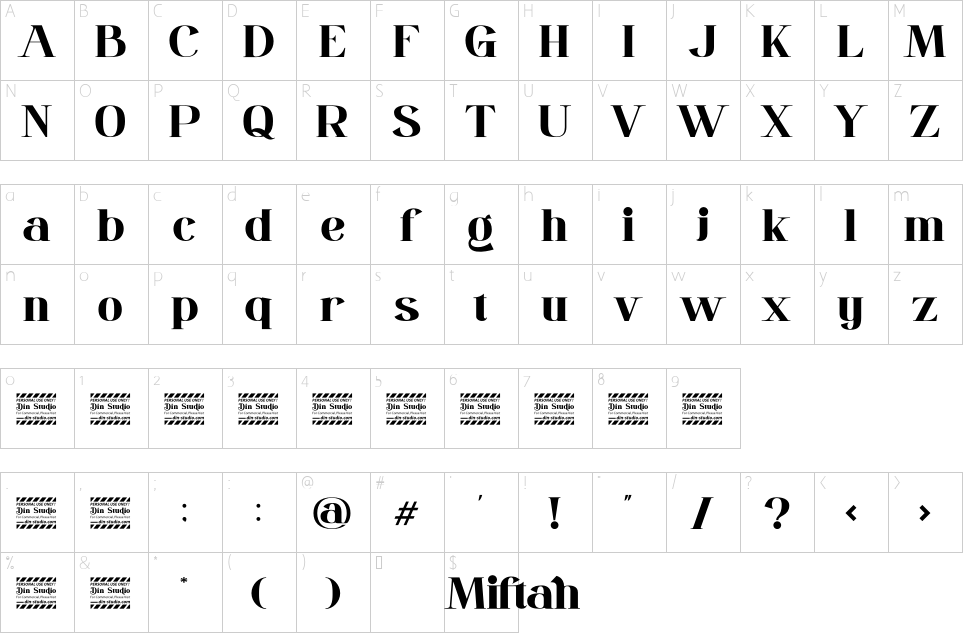
Descobrir uma nova fonte pode ser como uma aventura no mundo da gráfica. E aqui está Miftah, uma fonte grátis para Windows e Mac que foi cuidadosamente projetada pela Din Studio. Com um design cuidadoso e elegante, Miftah oferece uma variedade de opções para personalizar seus projetos digitais. Se você está à procura de uma fonte que combine facilidade de uso com um visual atraente, Miftah está aqui para oferecer exatamente o que você precisa. Desde o título de um site até o texto de um email, Miftah oferece uma gama de aplicações que garantem que sua comunicação digital seja tanto clara quanto atraente. Descubra por si mesmo o fascínio de uma fonte única e gratuita, e não se esqueça de dizer obrigado à Din Studio por compartilhar Miftah conosco.